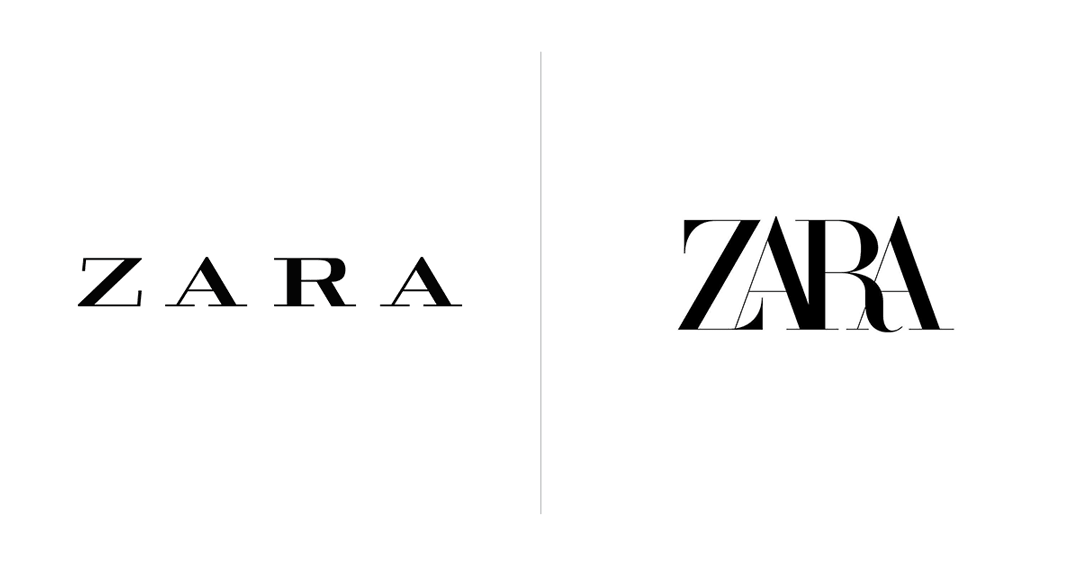
Zara renueva su logotipo y cambia su tipografía
La marca española utilizó el logo que aparecía en las etiquetas de sus prendas y lo convirtió en el logo principal.
Zara, la marca de ropa más popular de España, ha cambiado su logo principal por el que aparecía en las etiquetas de sus prendas. Ahora luce una nueva tipografía que junta más las letras que componen el nombre de la reconocida marca.
Zara es un ejemplo de dar la contra a la tendencia de grandes marcas que vuelven al minimalismo en los logos, prescindiendo de tildes, olvidando cursivas y sombras para hacerlos más sobrios y elegantes. La marca española lo ha hecho, pero con un toque más elaborado y barroco.